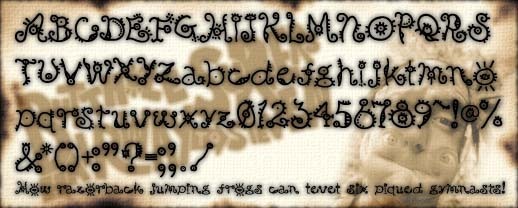
B Surfers Plane von Tohru Fukushima ist eine kostenlose Cartoon-Schrift, die jeden Buchstaben in eine kleine Kreatur verwandelt. Die B Surfers-Familie schlängelt sich mit tuscheartigen, handgezeichneten Schleifen, Stacheln und großen, starrenden „Augen“, die die Formen verzieren und deinem Text eine quirlige, leicht chaotische Energie verleihen. Es wirkt wie eine Kritzelei, die gerade von der Seite gekrochen ist – verspielt, eigenwillig und absolut lebendig.
Mit B Surfers Plane sprechen deine Überschriften nicht nur, sie winden sich. Diese kostenlose Schrift glänzt auf Konzertplakaten, Underground-Zines, Band-Logos, Halloween- oder Party-Flyern, Skateboard-Grafiken und auffälligen Social-Media- oder YouTube-Thumbnails. Wähle eine große Schriftgröße, damit die feinen Stacheln und Kringel gestochen scharf bleiben, und kombiniere sie mit einer schlichten, kompakten serifenlosen Schrift für den Fließtext, damit die wilde Typografie voll zur Geltung kommt.